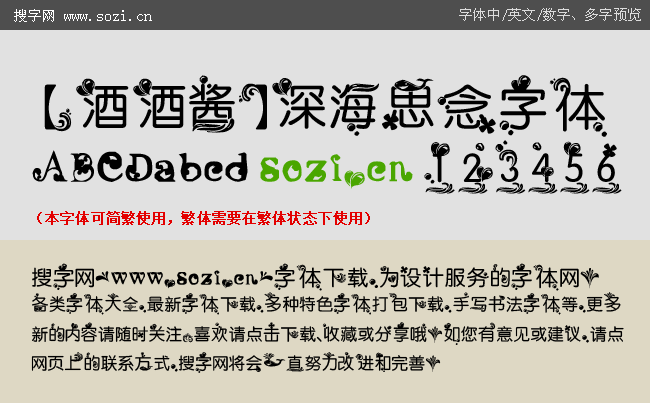
深海思念字體
搜字網(wǎng)給大家提供一款深海思念字體字體手機(jī)中文字體下載。這款手機(jī)字體是以圓體字體為原形,筆畫間嵌入了海洋元素等卡通圖案。在具備圓體清晰風(fēng)格的同時,卡通味也特別濃,是一款非常可愛的卡通字體,特別適合喜歡手機(jī)字體個性一些的朋友在手機(jī)上安裝使用。